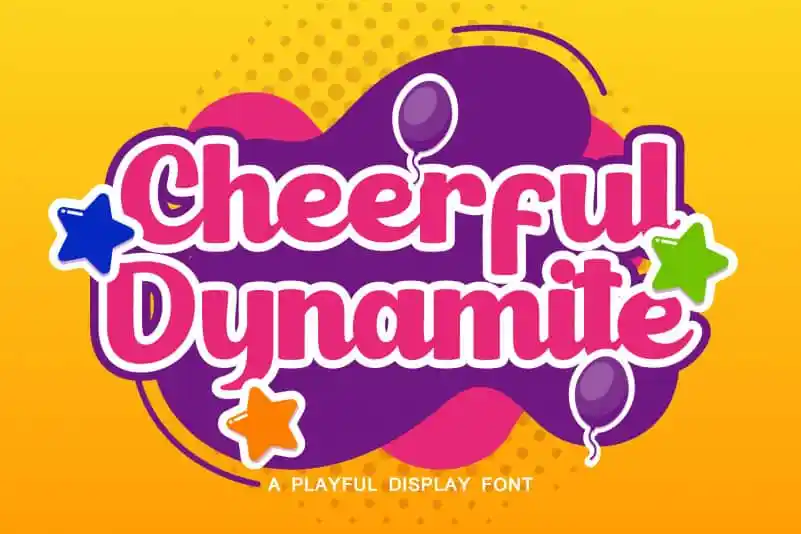
Cheerful Dynamite Bold Script Font – Download Grátis
A ‘Cheerful Dynamite Bold Script Font’ é uma seleção especial para aqueles que buscam uma fonte script com um toque leve e encantador. Criada cuidadosamente como um tipo personalizado, esta fonte tem a capacidade de se tornar uma verdadeira preferência, além do seu formato dinâmico e desenho elaborado. Ideal para ambientes onde um toque descontraído pode transformar qualquer design, sua presença casual é tão encantadora quanto é levemente descuidada. Seu charme natural lhe dá uma aparência de genuína simplicidade, tornando-o perfeito tanto para textos informais quanto para títulos grandiosos. É uma fonte versátil que se adapta facilmente a diversos ambientes e estilos, sendo perfeitamente adaptável a tudo, desde os mais discretos até aqueles brilhantes em destaque. A ‘Cheerful Dynamite Bold Script Font’ é perfeita para designers gráficos que buscam um toque animado e jovial em seus projetos. Seja você criando cartazes, design editorial ou até mesmo layouts digitais pessoais, esta fonte será uma ótima escolha para dar agradável vida aos seus trabalhos de design. A sua presença é tanto uma alegria quanto um convite à descontração, tornando-a perfeita para estilos de design que valorizam a simplicidade e a alegria.